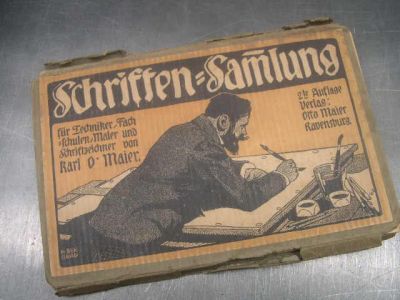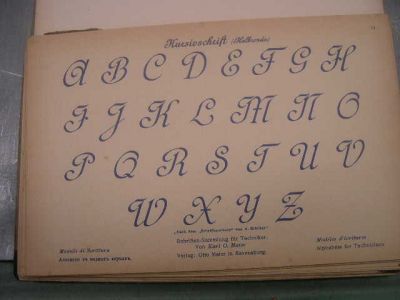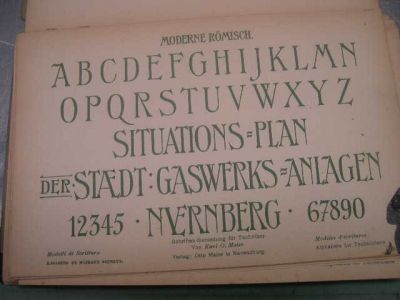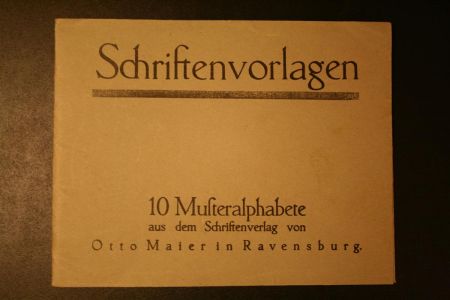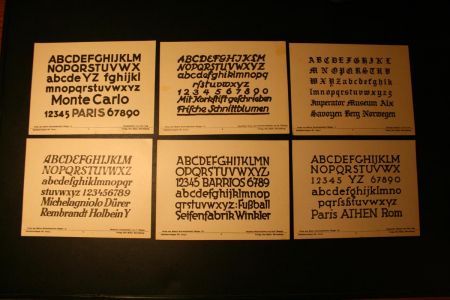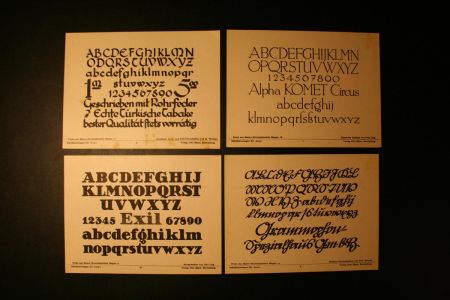
Die geheimen Ecken eines alten Hausrats
Vor ein paar Tagen fiel mir etwas in die Hände, was vor vielen Jahren mal meinem Großvater gehörte...
In dieser kleinen, schon etwas modrich richenden Mappe verbarg sich das:
Hier nochmal in groß:
Erfreut über diesen Fund mit sehr interessanten Schriften, interessiert es mich nun, wann das Mäppchen gedruckt worden ist und ob sich damit irgendwas in Verbindung bringen lässt.
Ein wirklich schöner Fund!
Wenn ich mich nicht täusche, firmiert der Verlag heute einfach unter dem Namen "Ravensburger" - zu der Zeit verlegte man im Haus dort auch die Werke von Tschichold und Itten.
Weis jemand von wann sie ungefähr ist?
... Wenn ich mich nicht täusche, firmiert der Verlag heute einfach unter dem Namen "Ravensburger" ...
Offiziell immer noch Otto Maier Verlag Ravensburg, aber du hast Recht, das sind die mit dem blauen Dreieeck rechts unten auf dem Umschlag. Heute machen die ihre beachtlichen Umsätze "nur" noch mit Puzzles, Spielen und Kinderbüchern (auch so TV-Zeugs, immer mal wieder), ihre Sachbuchsparte haben die vor ein paar Jahren verkauft. Aber dass die mal als "Schriftenverlag" firmiert haben, ist mir auch neu ... vor allem, wenn man sich deren heutige Typografie mal so anschaut.
Solche Musteralphabete wurden vor allem als Skizziervorlagen von Schildermalern verwendet. Zur Inspiration, vor allem aber auch für deren Ausbildung. Hierbei muß man wissen, daß der Beruf des Schildermalers ein hoch angesehener und typographischer war. In meinen Augen eher die professionelle - im Sinne von Vermarktung - des Schriftenzeichnens, der Kalligraphie etc. - also durchaus künstlerisch.
Diese Mappen sind sehr häufig viel älter als 1930. In den 30er und 40er Jahren gab es sie zwar auch noch, aber die ältesten, die ich kenne, stammen aus der Zeit vor dem 1. Weltkrieg.
Damals waren die Grenzen zwischen Schriften, die im Blei für den Buchdruck gegossen wurden und denselben Schriften, die als Vorlagen für z.B. Schildermaler verwendet wurden, noch fließend.
Dieses hier habe ich vor einigen Wochen verkauft. Es war das älteste, das mir je untergekommen ist. Aber ich weiß, daß es noch ältere gibt:
Zum Inhalt:
Schriften-Sammlung für Techniker aller Art Verlag Otto Maier, Ravensburg
Loseblatt-Sammlung, Einband zerfleddert, die Blätter selbst in altersgemäß befriedigendem Zustand. Erscheinungsjahr: vor 1914, ca. 60 Blatt.
Interessant da Gemeine-m mit dem Querstrich oben drauf, das wohl anzeigen sollte, daß es sich um ein Doppel-m handelt.
Meiner Meinung nach ist der ideelle Wert solcher Fundstücke viel höher als die paar Euro, die man damit machen kann. Ist doch ein echtes Stück Arbeitskultur.
Dieses hier habe ich vor einigen Wochen verkauft. Es war das älteste, das mir je untergekommen ist.